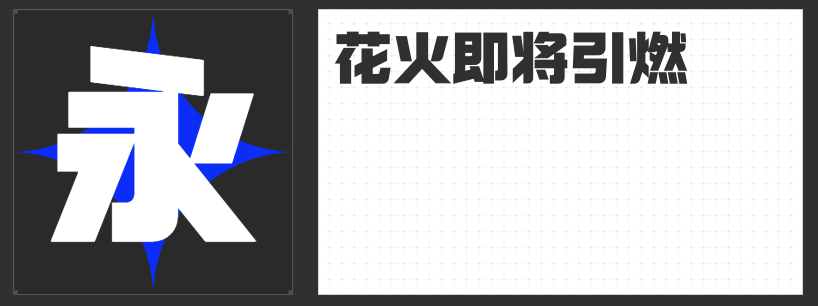
创意设计进阶指南:四款风格化字体解锁视觉新维度
在平面设计的语境中,字体不仅是信息载体,更是塑造氛围、传递情绪的核心元素。以下四款兼具艺术性与功能性的创意字体,以独特的笔形结构与文化基因,为设计师提供突破常规的视觉解决方案。
一、励字勇敢黑简 超黑
这款字体以几何化笔形构建视觉张力,摒弃所有衬线装饰,通过均匀的横竖笔画与钝角撇捺,形成如金属铸就的稳定感。其超黑字重赋予文字雕塑般的压迫感,却因笔划末端的钝化处理保持了阅读舒适度。设计师通过控制笔画粗细的绝对均衡,让文字在远距离场景中依然保持清晰辨识度,成为标题设计与品牌标志的利器。
二、造字侠磅礴简繁
取法传统碑帖的运笔节奏,这款字体在笔画粗细间制造戏剧性对比——主笔如横竖以浓墨重彩铺陈,副笔似撇捺则用飞白收束,形成“一波三折”的视觉韵律。转折处方圆并蓄的处理方式,既保留了书法的自然书写感,又通过几何化重构赋予现代设计语言。繁简体同步开发的设计思维,使其在文化类项目中具备更广泛的适用性。
三、造字侠热辣隶简
突破传统隶书的扁平结构,这款字体通过中宫适度收紧与笔画适度拉伸,创造出既庄重又灵动的视觉平衡。横笔的对称开张与竖钩的直线概括,将隶书的仪式感转化为现代设计语言;撇捺起收笔的粗细渐变处理,则暗合书法中的“一波三折”美学。这种对历史符号的解构重组,使其成为国潮设计、文化包装等场景的理想选择。
四、高手兵克侠客体
设计师从古建筑飞檐中提取灵感,将横笔画的起收笔转化为上扬的曲线,在规整的字形框架中注入动态基因。这种“以静制动”的设计策略,既保持了文字的易读性,又通过局部细节的夸张处理制造视觉记忆点。适度倾斜的笔画角度与均匀的字间距控制,让文字在排列时产生隐秘的韵律感,尤其适合需要传递复古情怀与文化厚度的项目。
这四款字体通过不同的设计路径——或强化力量感,或重构书写韵律,或融合古今美学,或解构建筑符号——为创意设计提供了多元化的表达工具。设计师可根据项目调性,选择与品牌基因最契合的视觉语言,让文字成为穿透视觉噪音的利器。